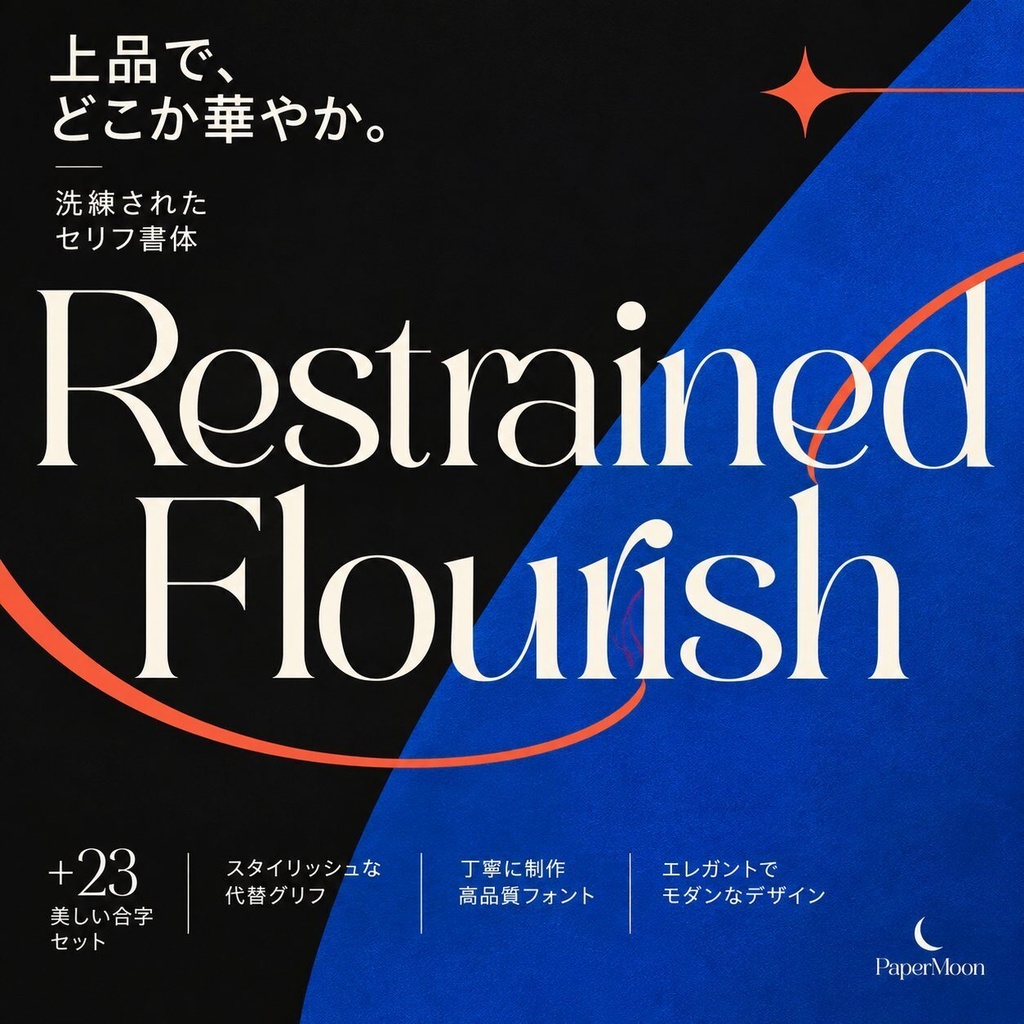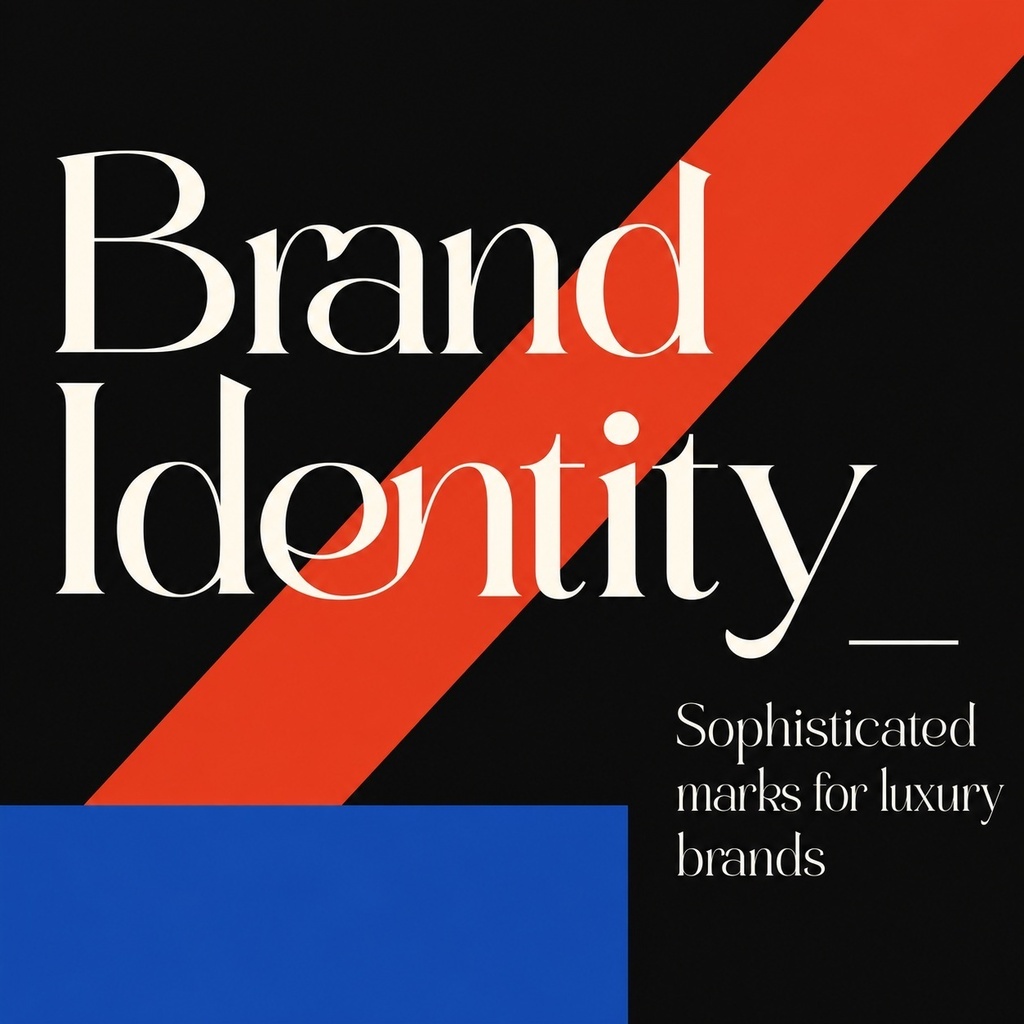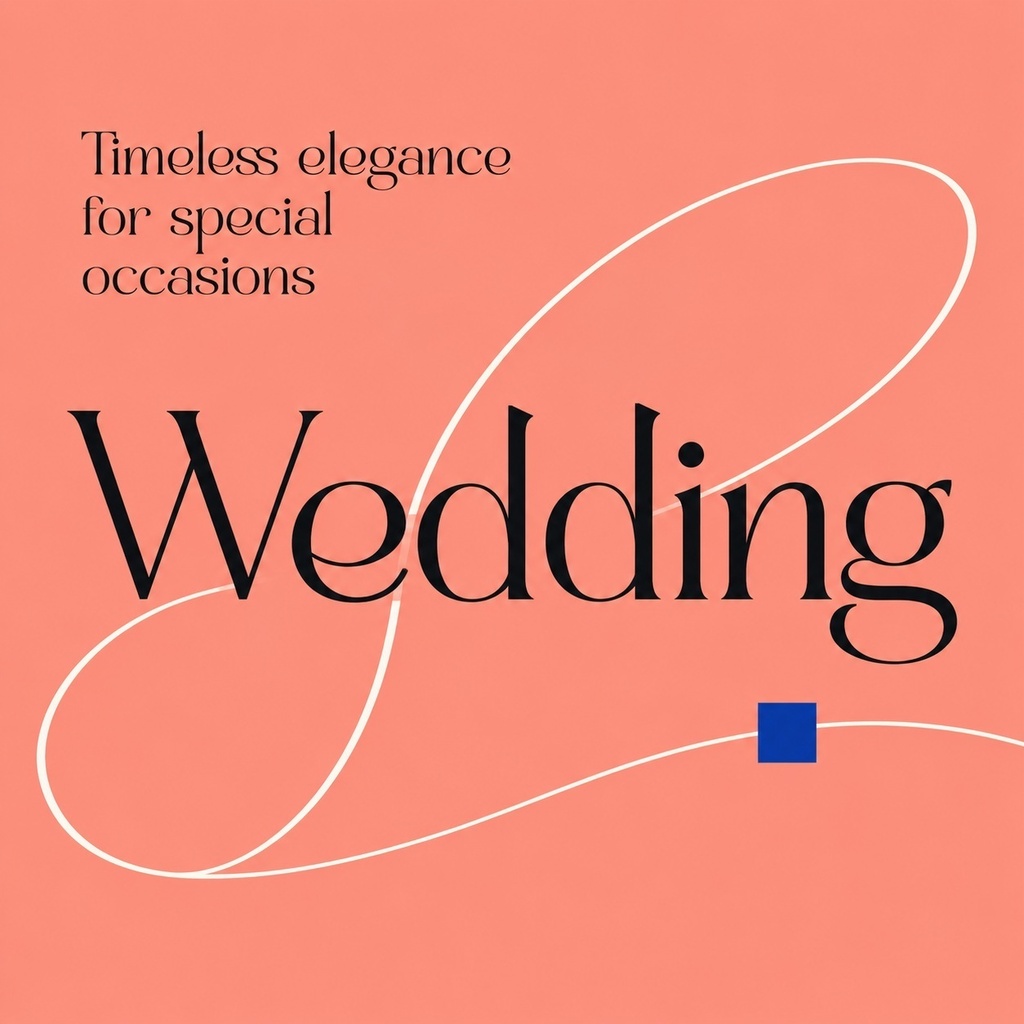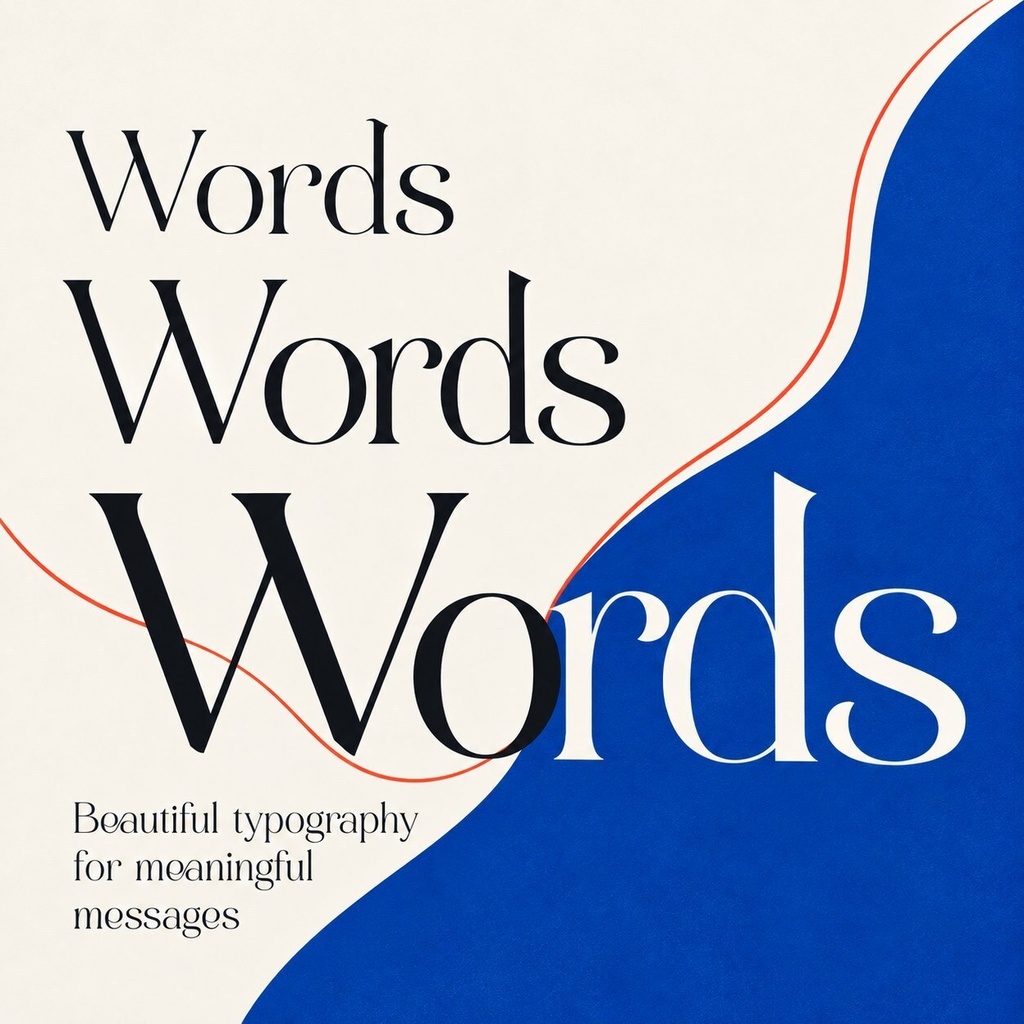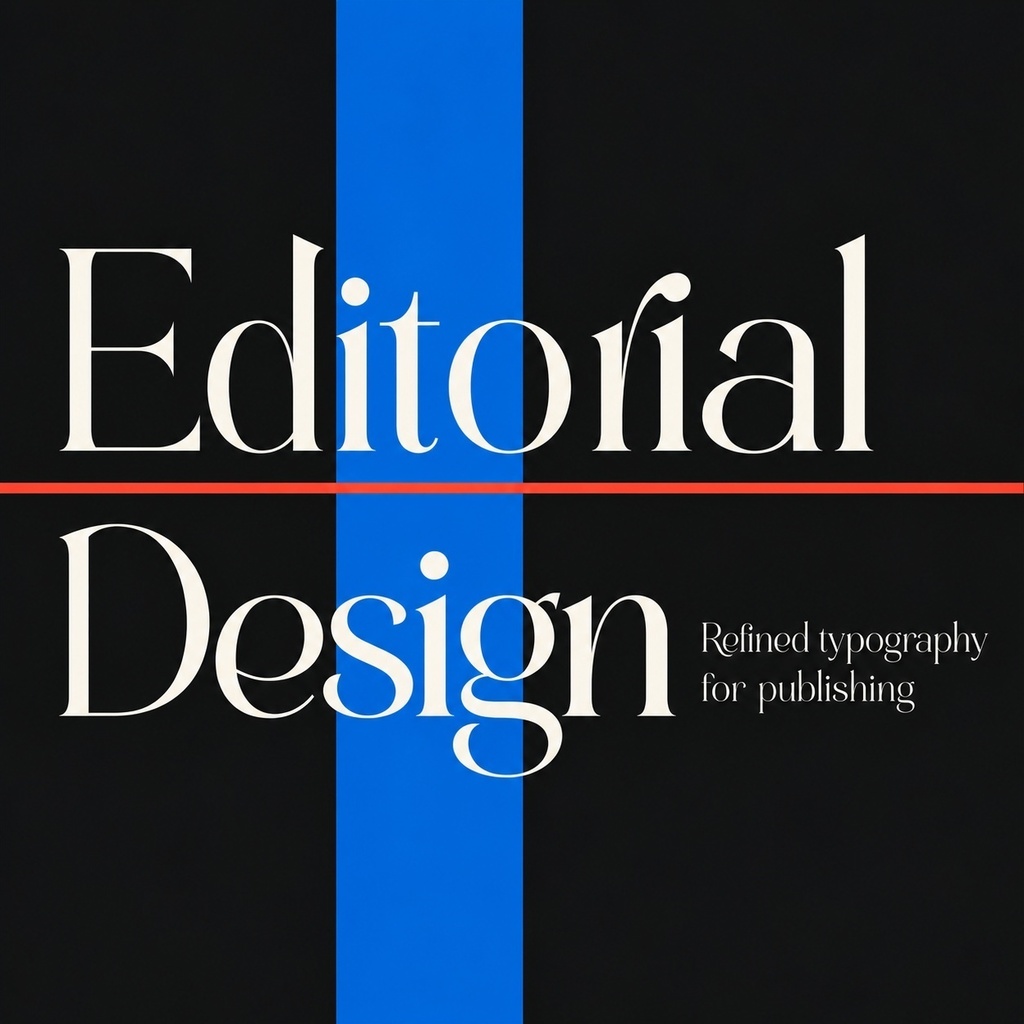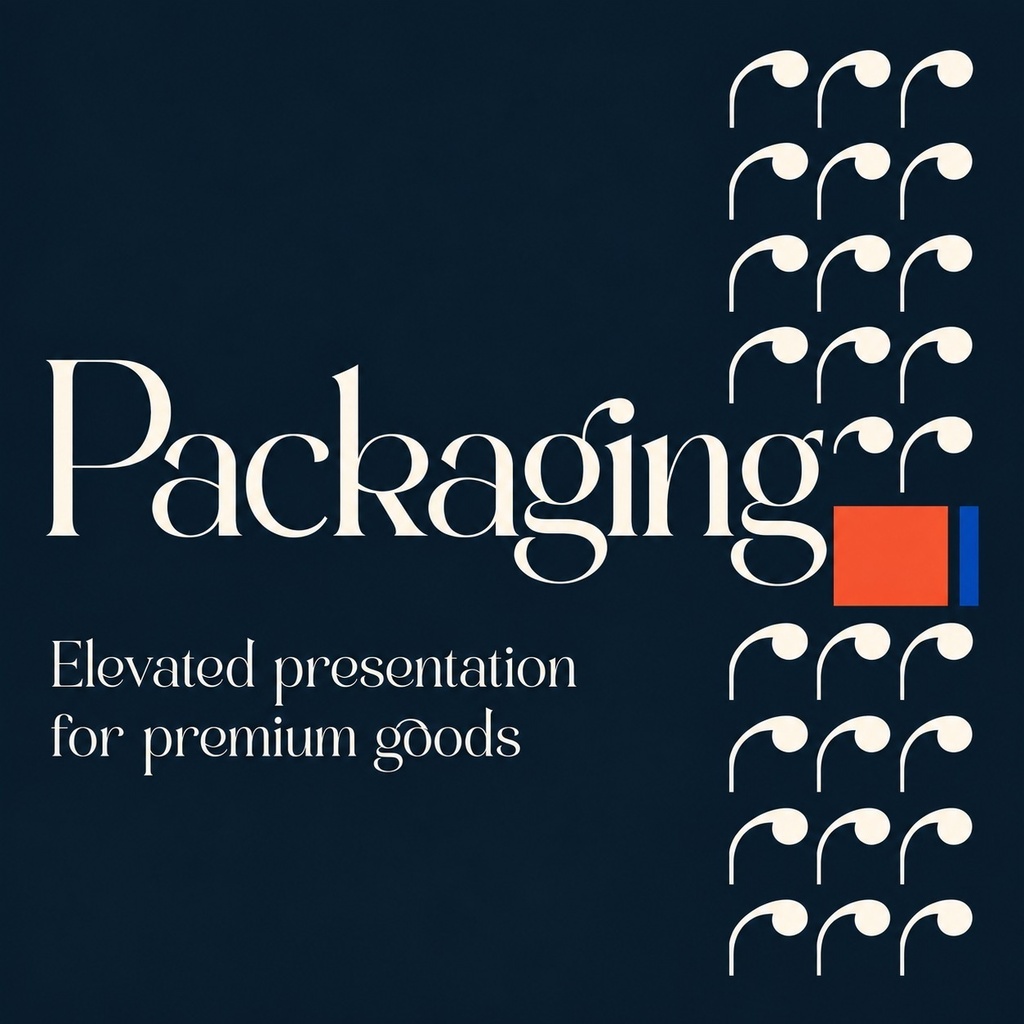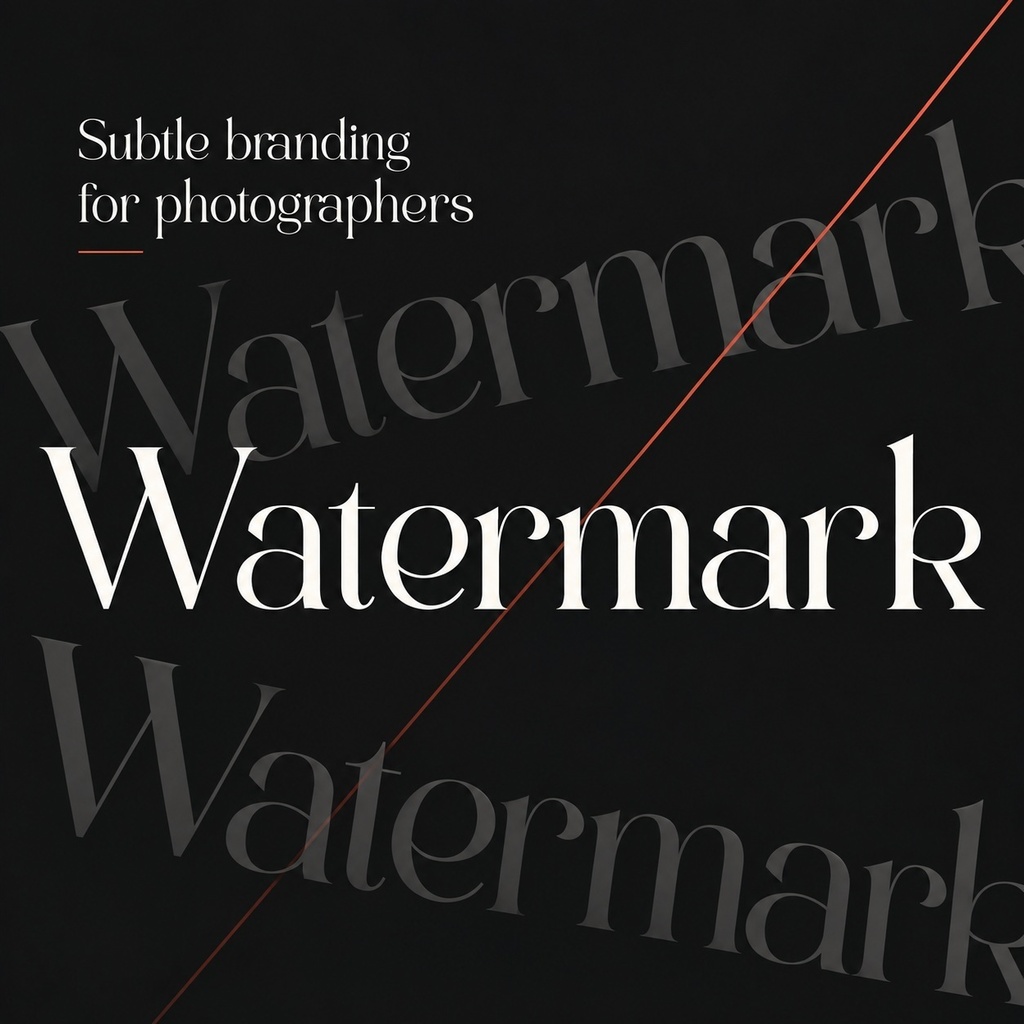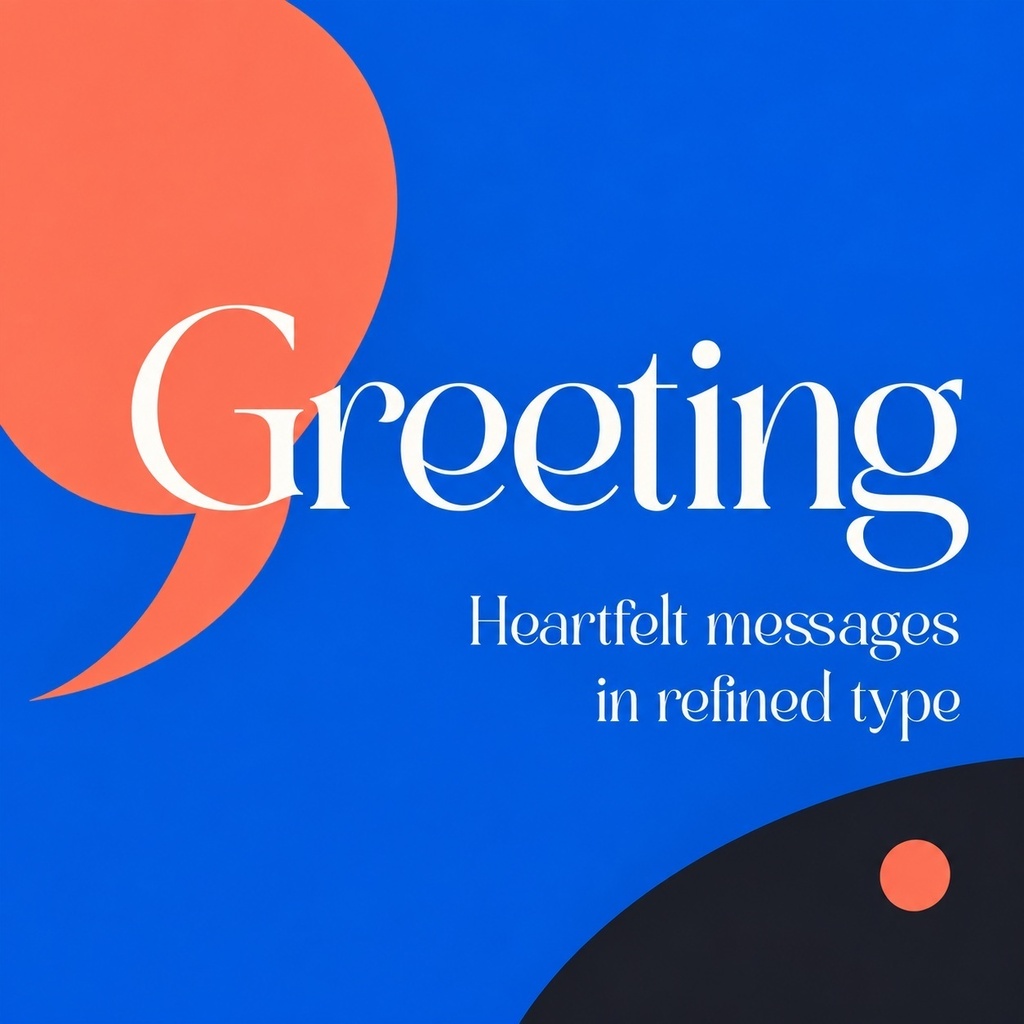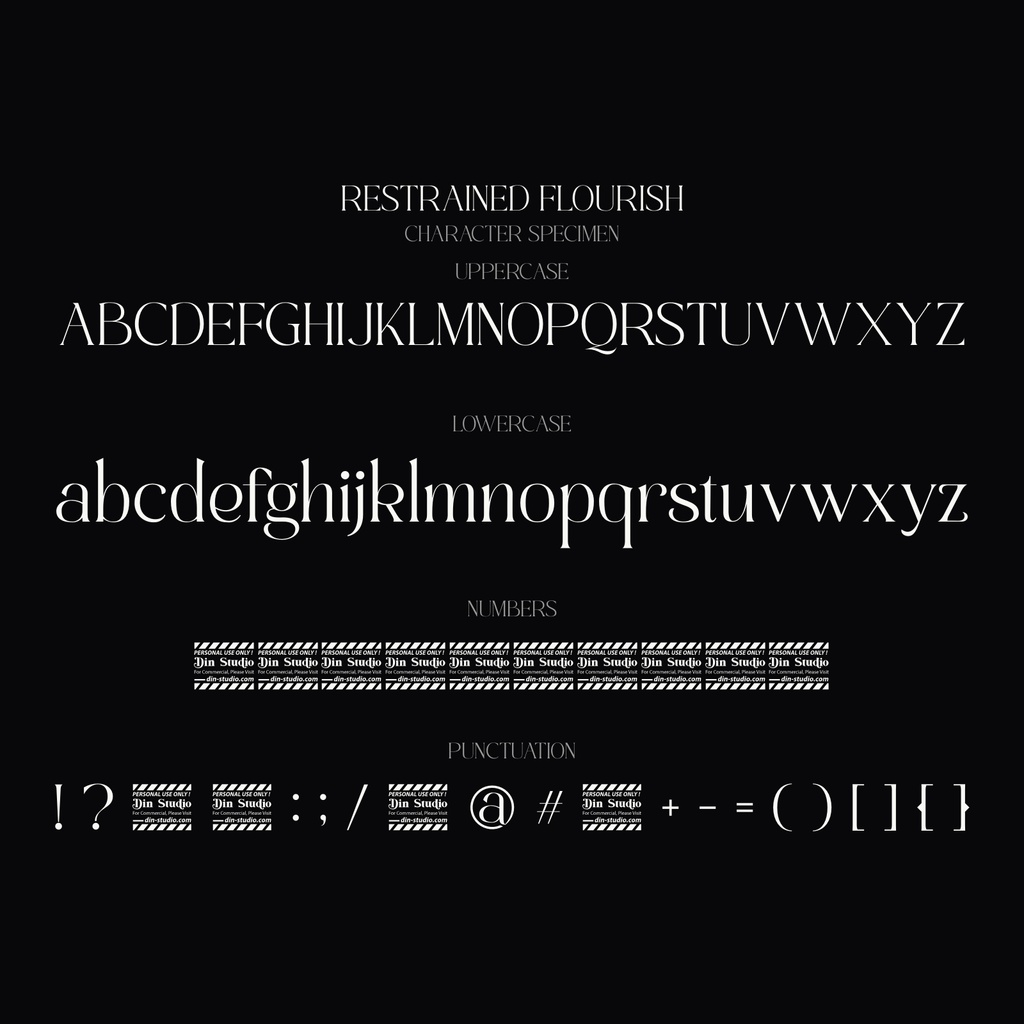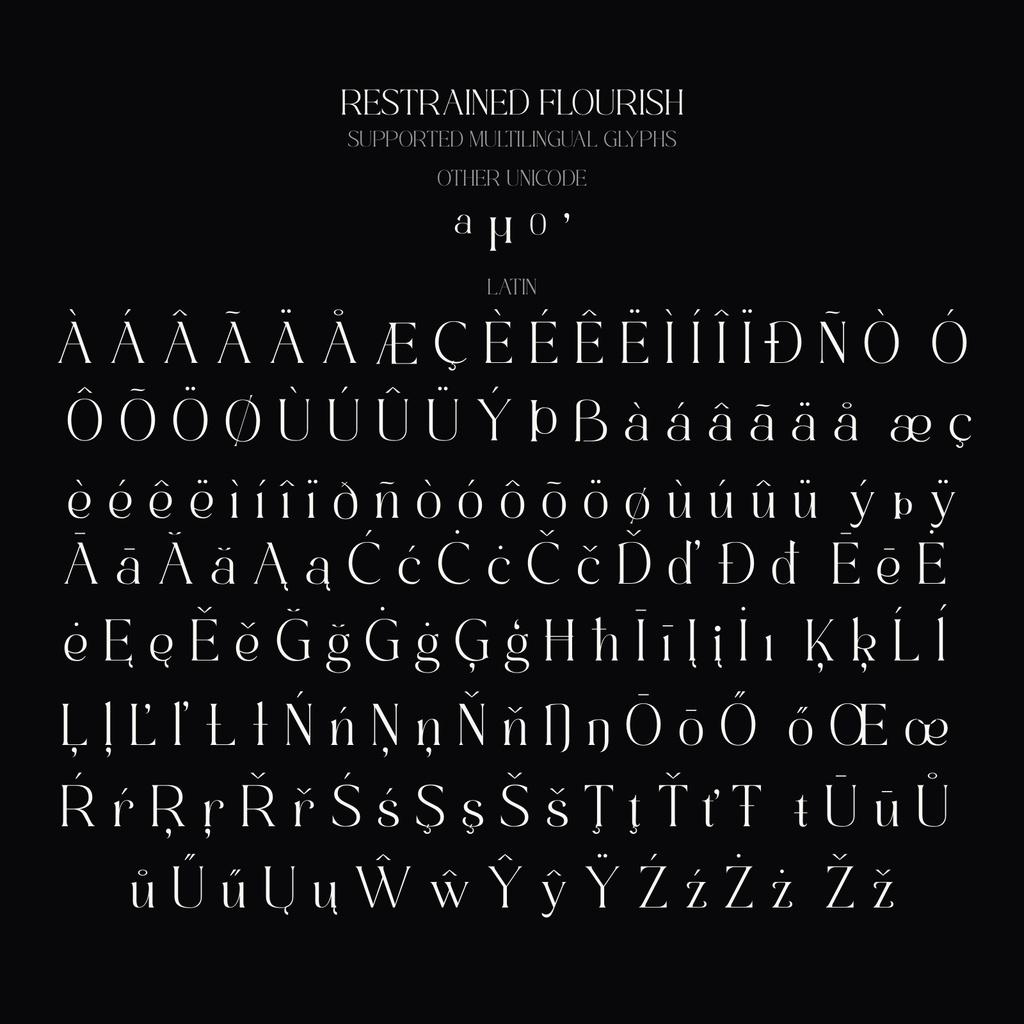
Restrained Flourish(リストレインド・フローリッシュ)【セリフフォント】
装飾的な筆致と洗練された曲線が特徴の、エレガントなセリフフォントです。ウェディング、ロゴ、コース、エディトリアル、高級ブランドのタイトルなど、上品さと格式を表現したい場面に最適です。 収録内容: - Regular (4スタイル) - Swash alternates (A-Z, a-z) - Initial caps (A-Z) - Ligatures ( fi, fl, ff, ffi, ffl ) - 460+グリフ / PUAエンコード対応 対応文字: 英語(A-Z, a-z)、数字(0-9)、基本記号 文字数: 460+グリフ 形式: OTF, TTF, WOFF, WOFF2 対応環境: - Adobe Photoshop/Illustrator/InDesign - Figma/Sketch - Microsoft Word/PowerPoint - Canva - その他のOpenType対応ソフトウェア 利用許諾: - 商用利用可: 広告、Web、印刷、ブランド、パッケージ、ゲーム等での利用可能 - 個人利用可: 学習、趣味、プライベートプロジェクト - 再配布・販売禁止 - テンプレートとしての再販禁止